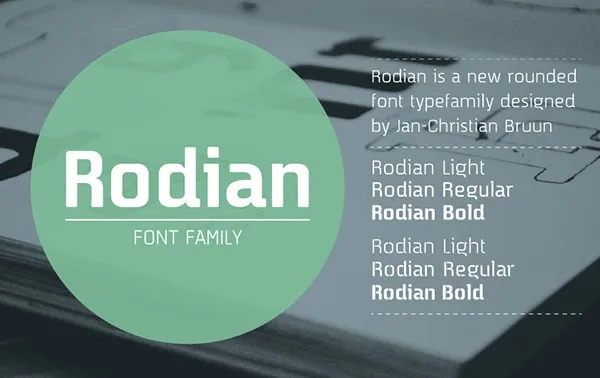
Rodian Sans Typeface – Fonte Grátis
Rodian Sans Typeface
A fonte Rodian Sans é uma criação de Hamilton que se inspirou no estilo moderno e arquitetônico das grandes cidades do mundo. Inspirada nos traços geométricos dos subterrâneos americanos e nas linhas limpas encontradas nos bairros urbanos, essa nova fonte tipo família foi projetada para expressar a sofisticação delicada de uma cidade moderna. Rodian Sans é o resultado da reaproximação de um antigo design pelo designer Jan-Christian Bruun. O processo de refino resultou em um novo formato mais contemporâneo e arredondado, mantendo os elementos suaves e um toque básico que fazem parte do DNA original de Rodian. O nome “Rodian” é uma referência a uma antiga história do cinema daneselândico onde um personagem chamado S.P.R.F. Rodian estava envolvido. Embora o nome seja desafiador para alguém não familiarizado com as tradições da cultura danesa, Hamilton usou essa fonte como base para criar algo que seja contemporâneo e acessível. A inspiração nesta fonte vem de uma fusão entre a simplicidade urbana e a essência arredondada do design original. Rodian Sans é perfeita tanto para aplicações digitais quanto para projetos gráficos tradicionais, oferecendo um equilíbrio perfeito entre a modernidade e o caráter sofisticado que faz dela uma fonte de escolha ideal para designers em busca de algo novo.